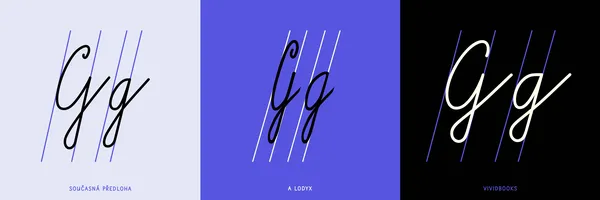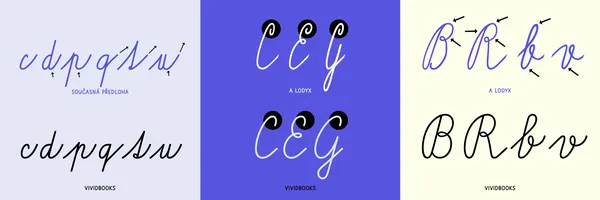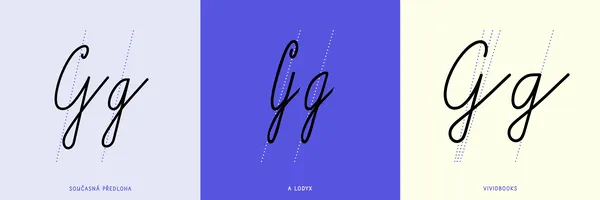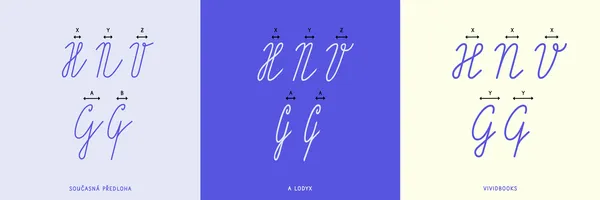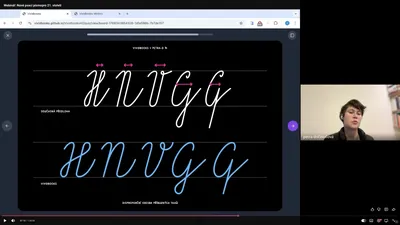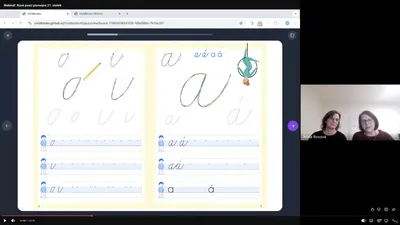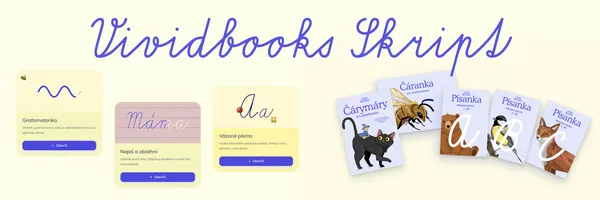
Vividbooks Skript
Společně s nakladatelstvím Vividbooks jsme pracovali na vývoji digitální aktualizace tradičního českého školního psacího písma! Výsledné písmo Vividbook Skript je jeho první významnou aktualizací od počátku 20. století. Cílem bylo aktualizovat kresbu písma a zachovat přitom tradiční předlohu rukopisu, jehož tvary používáme od  roku 1932 v podstatě beze změny, a přizpůsobit písmo potřebám a motorickým schopnostem dnešních dětí a kvalitní digitalizací také úrovni dnešních technologií.
Písmo Vividbooks Script si zachovává základní principy kurzívy – plynulost, rytmus a přirozené navazování znaků na sebe – a zároveň zavádí otevřenější, čitelnější a širší kresbu znaků se zjednodušenými tvary bez zbytečných ozdob a kudrlinek. Design se zaměřuje na zlepšení čitelnosti a snadnosti psaní a odstraňuje mechanické tvary, které neodrážejí přirozený pohyb ruky. Ve srovnání se stávajícím modelem se písmo vyznačuje velkorysejšími proporcemi, otevřenými smyčkami a celkově klidnější strukturou a harmonickou kresbou.
Písmo bylo vyvinuto exkluzivně pro Vividbooks, jeho potenciál však tkví v použití v širším kontextu: např. v domácím vzdělávání, kdy učitelé či rodiče vytvářejí doplňkové úkoly a materiály pro děti, jako jsou šablony na psaní, čtenářské deníky a podobně.
• Název fontu
Vividbooks Skript
• Statické řezy
(1) Regular
• Design písma
Petra Dočekalová
• Navrženo, vydáno v roce
2025, 2026
• Písmová klasifikace
School cursive, Monolinear, Script
• Celkový počet znaků
675
• Porovnání vylepšení
Níže vidíte srovnání mezi digitalizovanou verzí běžně používaného písma A lodyx, současným školním psacím písmem a novým skriptem Vividbooks, přičemž se zaměřte na klíčové aspekty, jakým jsou např.: sjednocený sklon všech znaků; úprava šířkových proporcí všech znaků; sjednocení rozdílů mezi tvaroslovím identických, příbuzných i odlišných znaků; odstranění nadbytečností – zejména ve smyčkách a v kudrlinkách; odstranění nepřesností a nesrovnalostí nejen v příbuzných detailech; odstranění problémů s plynulým navazováním znaků; vylepšení spojování znaků vyváženými mezerami a prostrkáním; precizní kvalita křivek, pečlivá kontrola, testování a celkově technicky kvalitní digitalizace.
Psací písmo Vividbooks staví na mém dlouhodobém zájmu a výzkumu českého rukopisu, který se vyvíjel během mého magisterského a doktorského studia na UMPRUM a jejich výstupů. Písmo Vividbooks představuje jistý mezikrok – aktuální fázi v pokračujícím procesu vytváření propracovanějšího a z hlediska jemné motoriky, typografie, metodiky výuky psaní a praxe s jednotlivými žáky co nejvhodnějšího a současnosti poplatného kurzívního písma pro budoucí prvňáčky, na kterém pracuji na pozadí…
Skicy a korektury
Na písmu Vividbooks Skript jsme spolupracovali společně s Annou Rosovou a Kateřinou Machovou Ondřejovou několik měsíců, během nichž jsme si vyměňovaly celou řadu korektur a připomínek vyvstávajích nejen z celého procesu, ale také přicházejících od jednotlivých učitelů a konzultantů Vividbooks. Snažily jsme se zapracovat co nejvíce připomínek a poznatků i od dalších odborníků a specialistů, a i po jeho vydání počítáme s tím na písmu aktivně dále pracovat a všechny připomínky a úpravy případně řešit písmo podle toho, co ukáže samotná „praxe“.